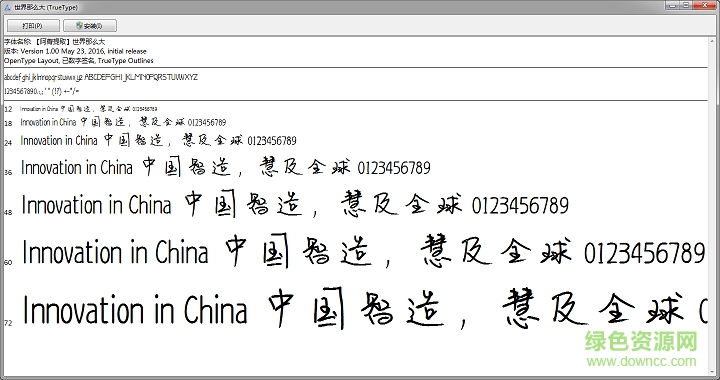
方正“世界那么大”字體包是根據(jù)網(wǎng)絡(luò)流行語“世界那么大,我想去看看”制作的特色字體。綠色字體網(wǎng)提供的為世界那么大體ttf完整版,喜歡的朋友,趕快拿走吧!
還記得那封紅爆網(wǎng)絡(luò)的辭職信嗎?“世界那么大,我想去看看”,這封“史上最具情懷的辭職信”作者顧少?gòu)?qiáng)的同款手寫字體包新鮮出爐啦,出自文藝女神之手的字體線條流暢、灑脫帥氣,是骨子里自帶不羈性格文藝范兒們的不二之選!
手寫風(fēng)格的鋼筆字體,字體書寫流暢,瀟灑大方,整體效果十分出色。